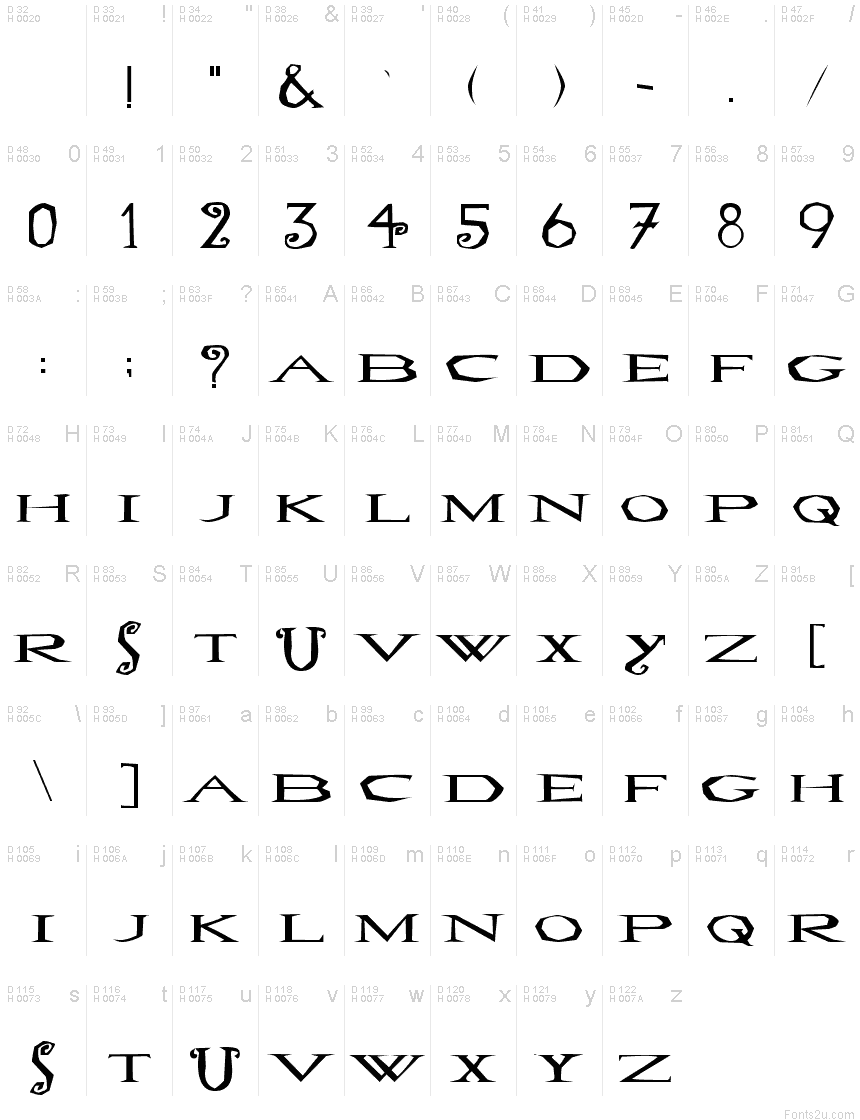
LoveSexy, odświeżony przez Kurta Knoppa w 1996 roku, to bezpłatny ozdobny krój pisma z nutką figlarności, łączący klimat późnych lat 80. z Art Nouveau. Litery łączą ostre kliny i szerokie szeryfowe kształty z kilkoma teatralnymi akcentami, co najwyraźniej widać w zaokrąglonym, wielokątnym O oraz zawijanym S, dzięki czemu alfabet sprawia wrażenie „wystrojonego”, a nie tylko pogrubionego.
Pasuje do plakatów, okładek albumów, ulotek modowych, brandingu klubów nocnych i nagłówków, w których tytuł potrzebuje odrobiny charakteru, nie stając się przy tym tylko ciekawostką. Jako darmowy font, LoveSexy świetnie sprawdza się również w monogramach, krótkich wizytówkach i inicjałach, ponieważ te zakręcone i wycięte formy najlepiej prezentują się, gdy mają przestrzeń do zaprezentowania swojego stylu.